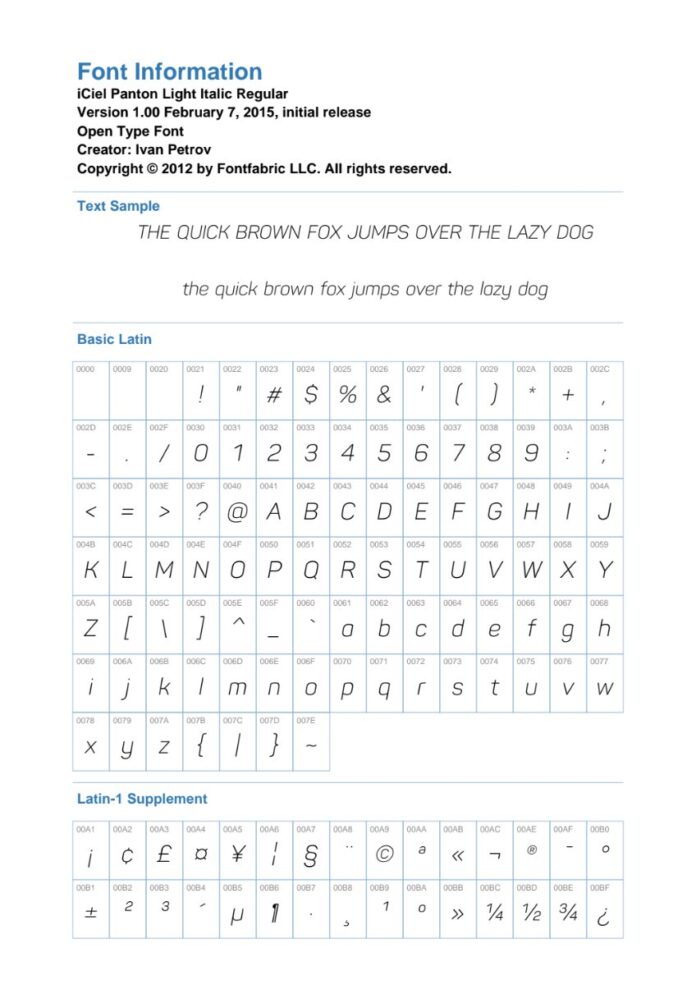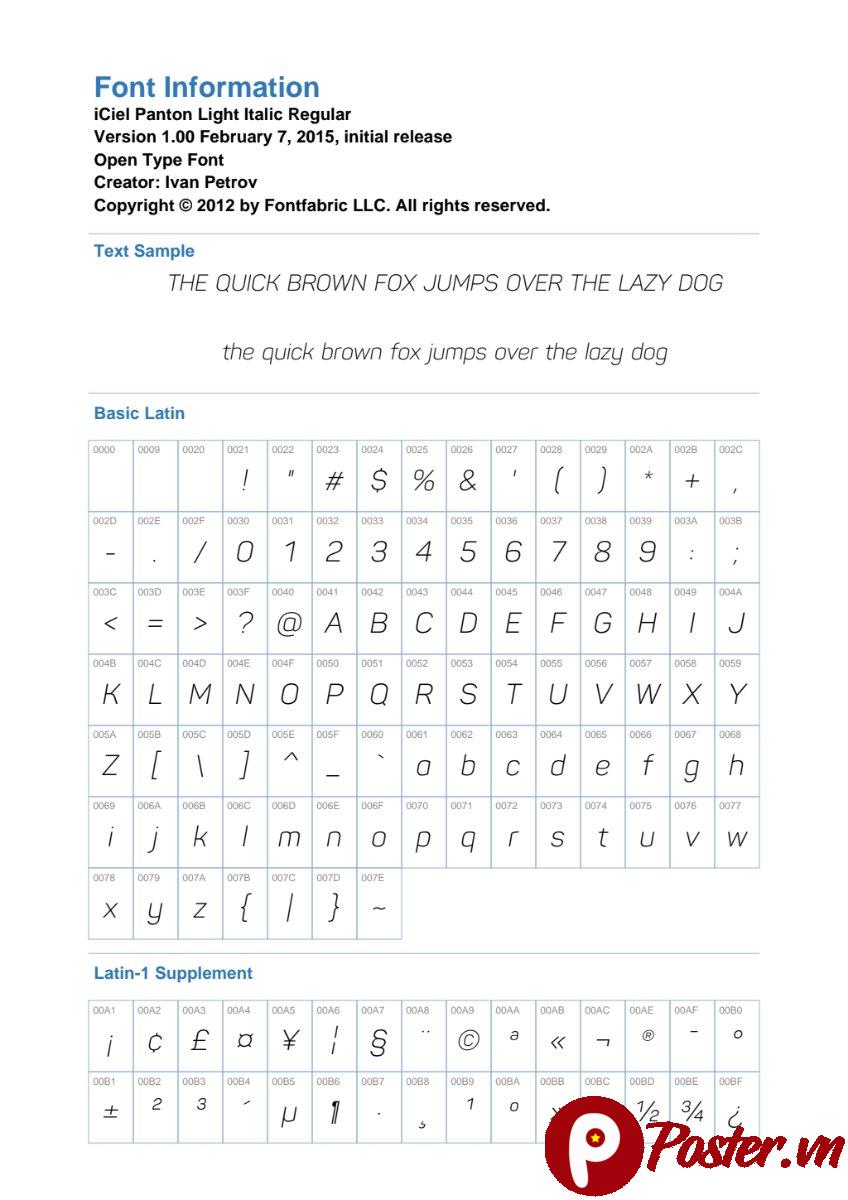
Giới thiệu về Font iCiel Panton Light Italic
Font iCiel Panton Light Italic là một kiểu chữ hiện đại, thanh lịch, được thiết kế bởi Ivan Petrov và phát hành bởi Fontfabric LLC. Với phong cách nghiêng nhẹ nhàng và độ dày ‘Light’, font này mang đến sự tinh tế, chuyên nghiệp cho mọi thiết kế. Đây là lựa chọn lý tưởng cho các dự án cần sự sang trọng nhưng vẫn giữ được nét hiện đại.
Đặc điểm nổi bật của Font iCiel Panton Light Italic
- Thiết kế thanh lịch: Với các đường nét mỏng, nghiêng nhẹ, font chữ này tạo cảm giác mềm mại, uyển chuyển.
- Tính ứng dụng cao: Phù hợp cho nhiều loại hình thiết kế như logo, tiêu đề, ấn phẩm quảng cáo, website, tạp chí và nhiều hơn nữa.
- Dễ đọc: Mặc dù là kiểu chữ nghiêng, iCiel Panton Light Italic vẫn đảm bảo khả năng đọc tốt, không gây mỏi mắt cho người xem.
- Hỗ trợ đa ngôn ngữ: Bao gồm các ký tự Latin cơ bản và bổ sung, giúp bạn linh hoạt hơn trong các dự án quốc tế.
Ứng dụng của Font iCiel Panton Light Italic trong thiết kế
Font iCiel Panton Light Italic có thể được sử dụng trong vô số các ứng dụng thiết kế khác nhau, từ những dự án cá nhân đến các chiến dịch thương mại lớn. Sự linh hoạt và vẻ đẹp của nó làm cho nó trở thành một công cụ không thể thiếu cho các nhà thiết kế đồ họa.
Thiết kế thương hiệu và quảng cáo
Trong lĩnh vực xây dựng thương hiệu, font iCiel Panton Light Italic là lựa chọn tuyệt vời cho logo, slogan và các tài liệu marketing. Nó giúp truyền tải thông điệp về sự tinh tế, sang trọng và chuyên nghiệp của thương hiệu. Đối với các ấn phẩm quảng cáo như banner, poster, flyer, font này sẽ thu hút ánh nhìn và tạo ấn tượng mạnh mẽ.
Thiết kế website và ứng dụng
Với sự phát triển của công nghệ số, việc lựa chọn font chữ phù hợp cho website và ứng dụng di động là vô cùng quan trọng. iCiel Panton Light Italic mang lại vẻ đẹp hiện đại, giúp giao diện người dùng trở nên thân thiện và dễ chịu hơn. Nó đặc biệt phù hợp cho các tiêu đề, menu và các đoạn văn bản ngắn cần sự nổi bật.
Thiết kế ấn phẩm in ấn
Từ bìa sách, tạp chí, thiệp mời đến bao bì sản phẩm, font iCiel Panton Light Italic đều có thể phát huy tối đa vẻ đẹp của mình. Nó tạo ra sự hài hòa, cân đối và làm tăng giá trị thẩm mỹ cho các sản phẩm in ấn. Đặc biệt, với các thiết kế mang phong cách tối giản (minimalist), font này sẽ là điểm nhấn hoàn hảo.
Hướng dẫn sử dụng Font iCiel Panton Light Italic hiệu quả
Để tận dụng tối đa vẻ đẹp của font iCiel Panton Light Italic, bạn cần lưu ý một số điểm sau:
Kết hợp với các font chữ khác
Font iCiel Panton Light Italic thường được sử dụng làm tiêu đề hoặc điểm nhấn. Khi kết hợp với các font sans-serif hoặc serif cơ bản cho phần nội dung, nó sẽ tạo ra sự cân bằng và dễ đọc. Hãy thử nghiệm với các cặp font khác nhau để tìm ra sự kết hợp ưng ý nhất cho dự án của bạn.
Lựa chọn kích thước và màu sắc phù hợp
Do là font ‘Light’ và nghiêng, bạn nên sử dụng iCiel Panton Light Italic ở kích thước đủ lớn để đảm bảo độ rõ nét. Về màu sắc, font này rất linh hoạt và có thể kết hợp với nhiều bảng màu khác nhau. Tuy nhiên, để tôn lên vẻ đẹp thanh lịch, bạn nên ưu tiên các màu sắc trung tính hoặc pastel.